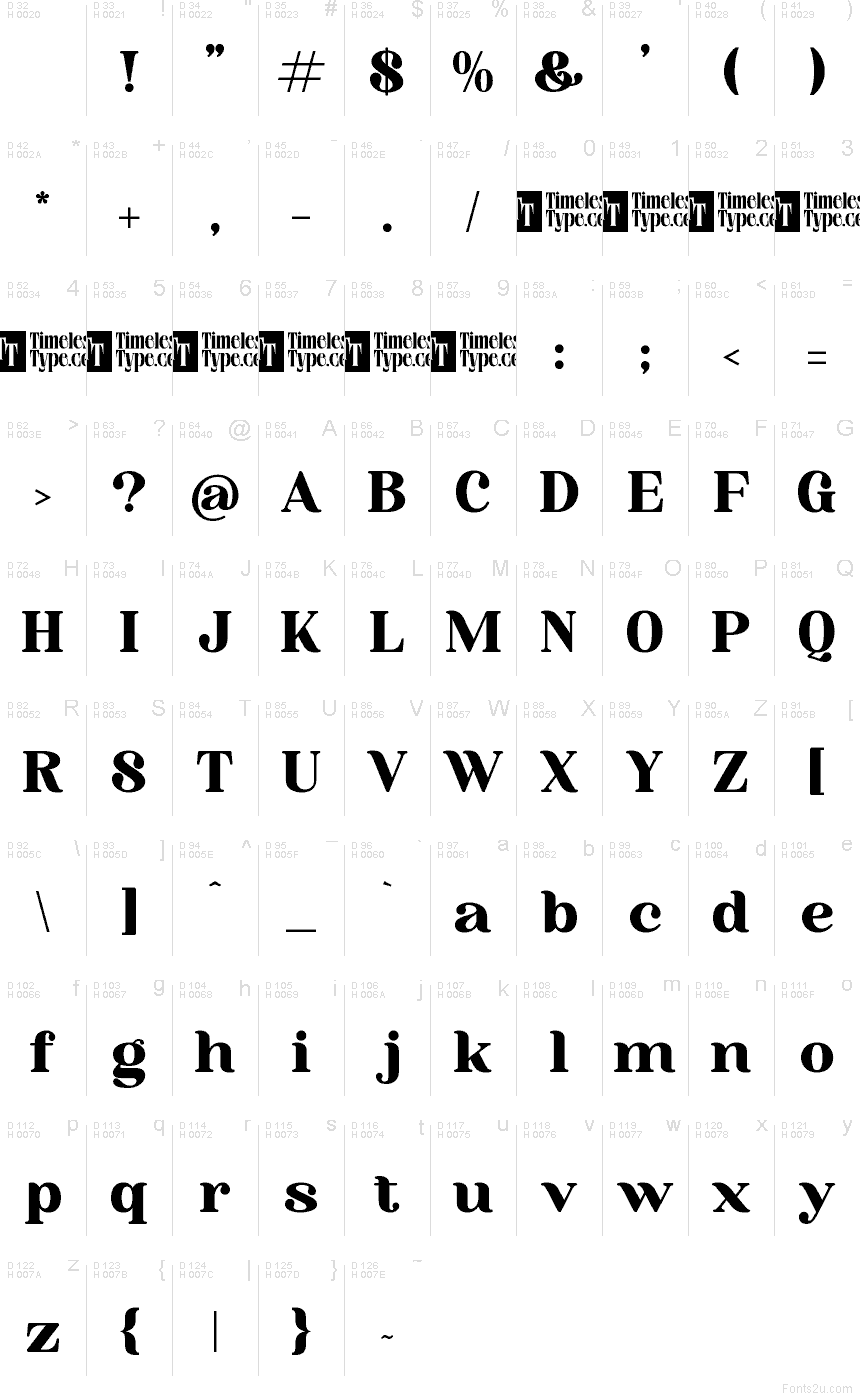
Eleve seus projetos de design com Font Madrid & Birch - Modern Alternate Serif Display, uma fonte que une a elegância clássica a uma essência contemporânea. Esta serifada de alto contraste oferece uma presença sofisticada e marcante, ideal para composições que exigem calor humano e forte impacto visual. Suas curvas meticulosamente desenhadas e serifas expressivas exalam um luxo refinado que atrai o olhar de imediato.
Alcance uma versatilidade criativa sem igual com o extenso conjunto de recursos de Font Madrid & Birch - Modern Alternate Serif Display. Com uma rica seleção de glifos alternativos e ligaduras impressionantes, esta tipografia capacita designers a compor uma identidade gráfica verdadeiramente única e memorável. De títulos de grande destaque a subtítulos cheios de personalidade, sua flexibilidade assegura o mais alto impacto estilístico, diferenciando a sua marca.
Conquiste ressonância internacional com total naturalidade com Font Madrid & Birch - Modern Alternate Serif Display. Graças ao seu amplo suporte multilíngue, Font Madrid & Birch - Modern Alternate Serif Display se adapta com perfeição aos mercados globais, revelando-se extremamente versátil para projetos internacionais. Essa capacidade garante que a voz da sua marca preserve a sofisticação e a clareza planejadas, ampliando o seu alcance.
Um recurso indispensável onde a distinção é fundamental, Font Madrid & Birch - Modern Alternate Serif Display é a escolha ideal para marcas de luxo, design editorial de alto padrão e embalagens de produtos premium. Imagine sua estética enriquecendo revistas de moda, convites exclusivos ou cabeçalhos elegantes de sites. Escolha esta fonte para causar uma impressão inesquecível e imprimir em seus trabalhos uma elegância moderna e atemporal.